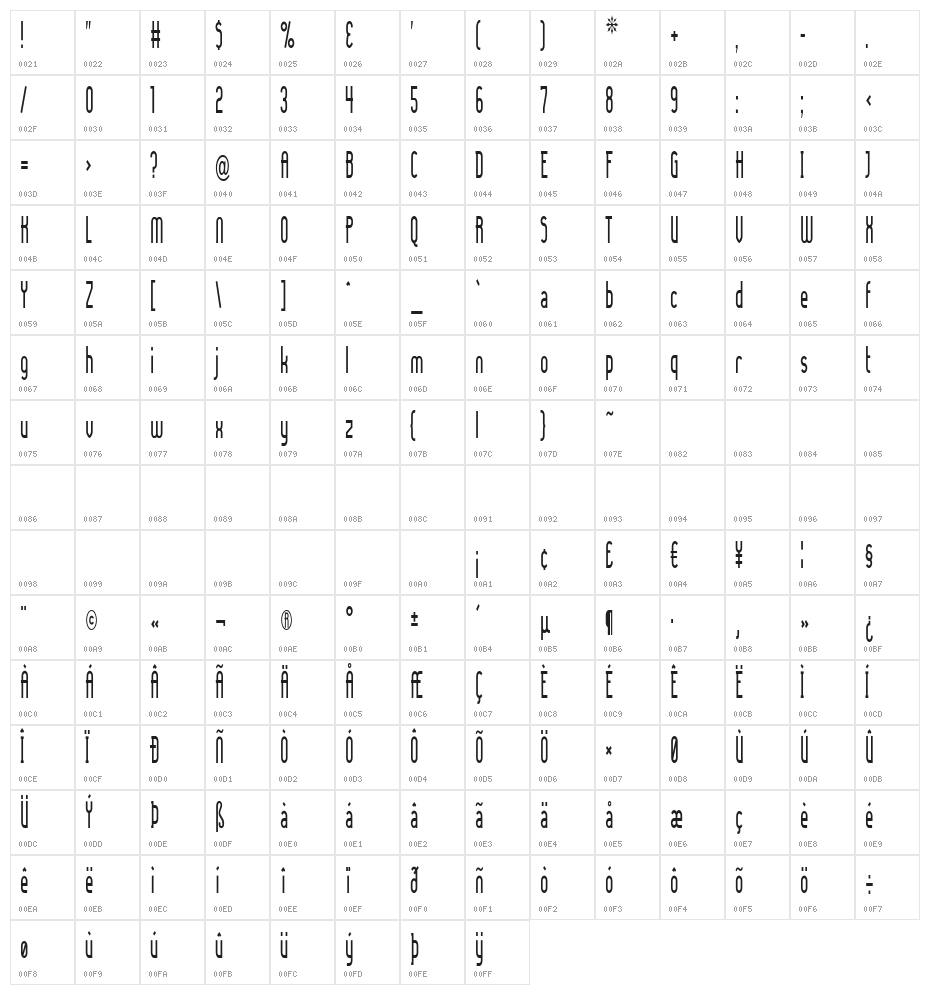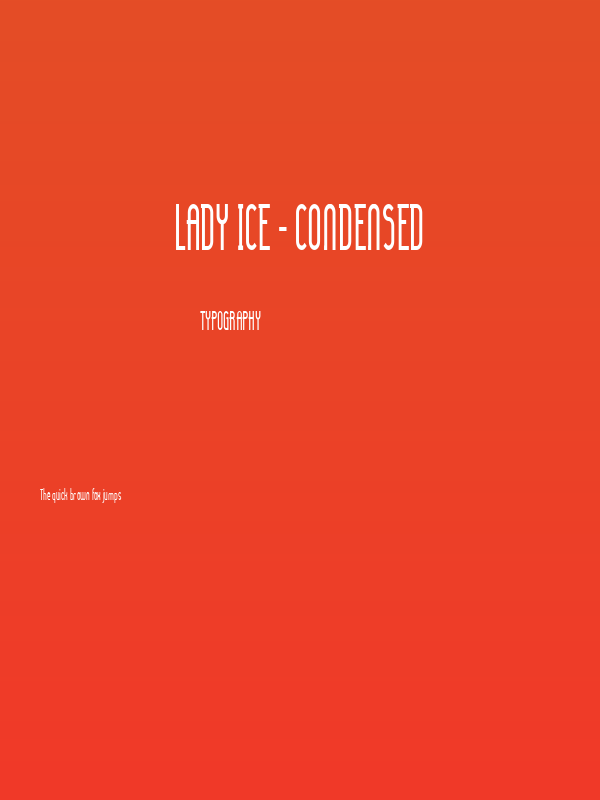
Lady Ice - Condensed Font
| Vorgeschlagene Projekte | Ideal for branding, editorial design, posters, and digital media where a modern and sophisticated look is desired. |